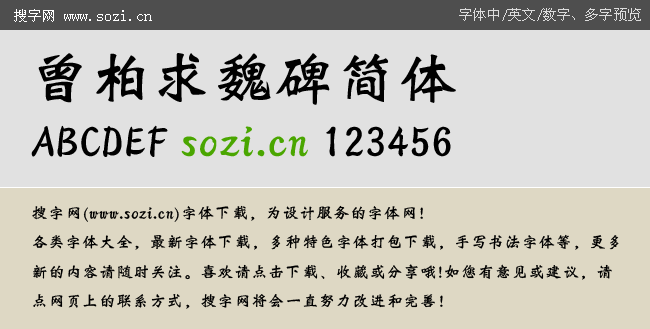
方正字跡-曾柏求魏碑簡(jiǎn)體
搜字網(wǎng)給大家提供一款方正字跡-曾柏求魏碑簡(jiǎn)體中文字體下載。方正字跡-曾柏求魏碑簡(jiǎn)體是一款非常漂亮的魏碑字體,字形流暢大方,效果十分漂亮。此款字體適用于包裝設(shè)計(jì)、廣告設(shè)計(jì)、海報(bào)設(shè)計(jì)等視覺(jué)環(huán)境。
• 風(fēng)格類別: 魏碑